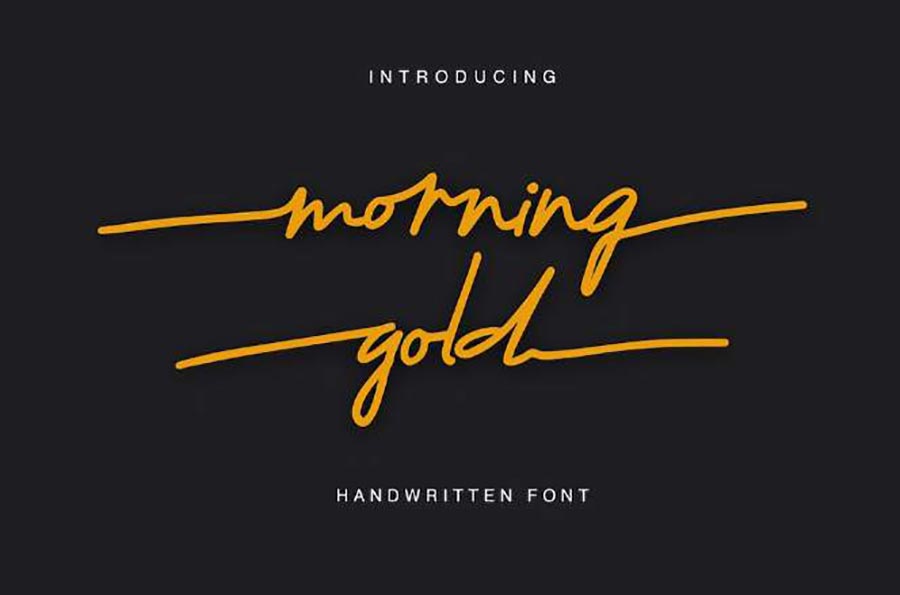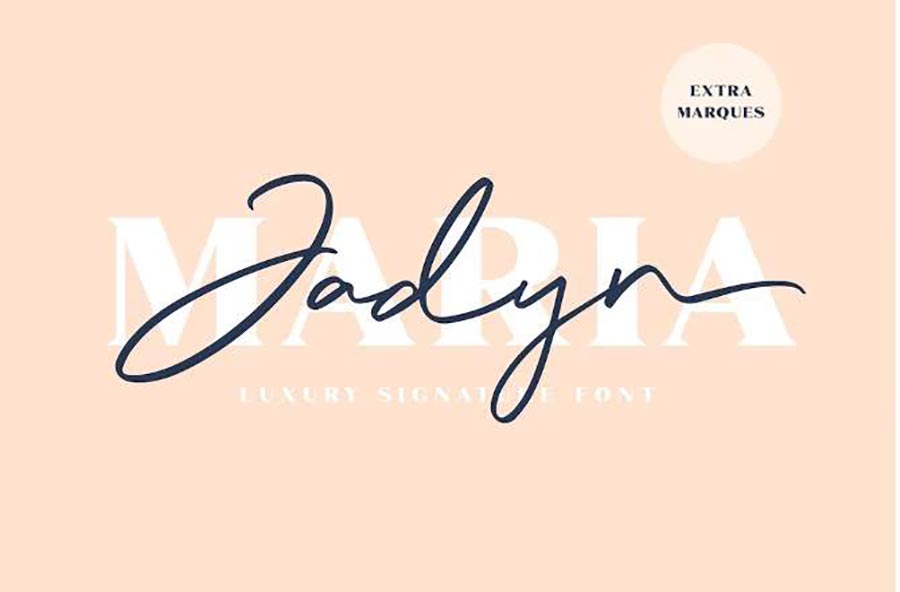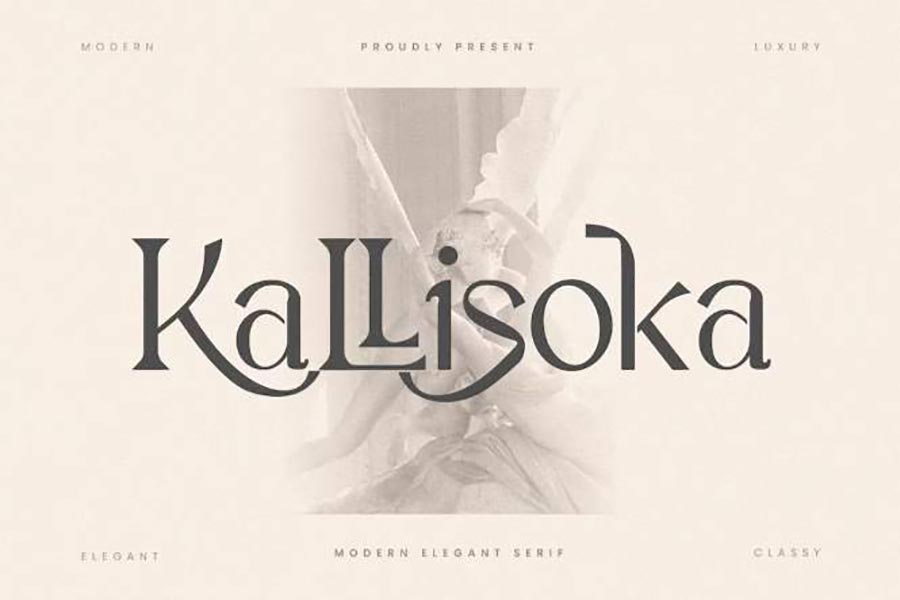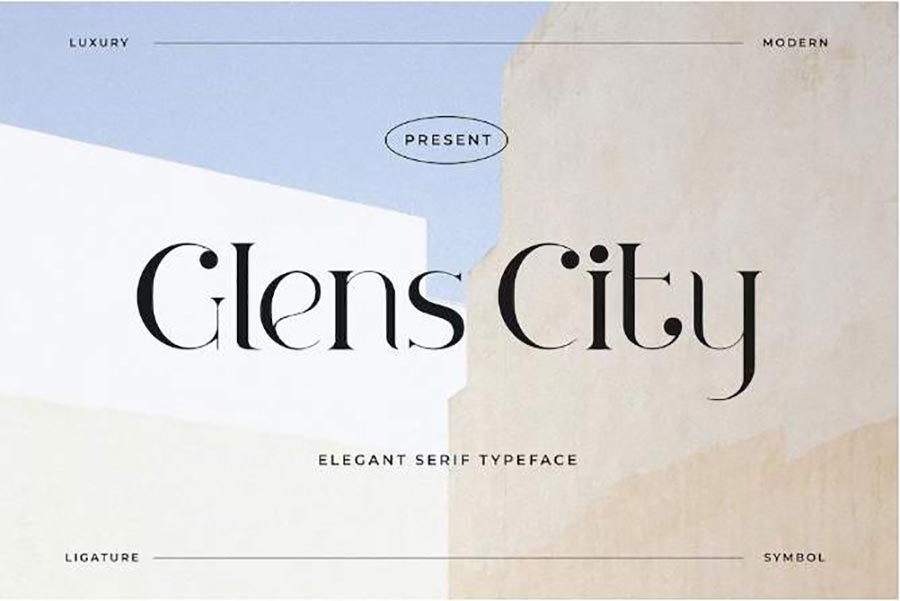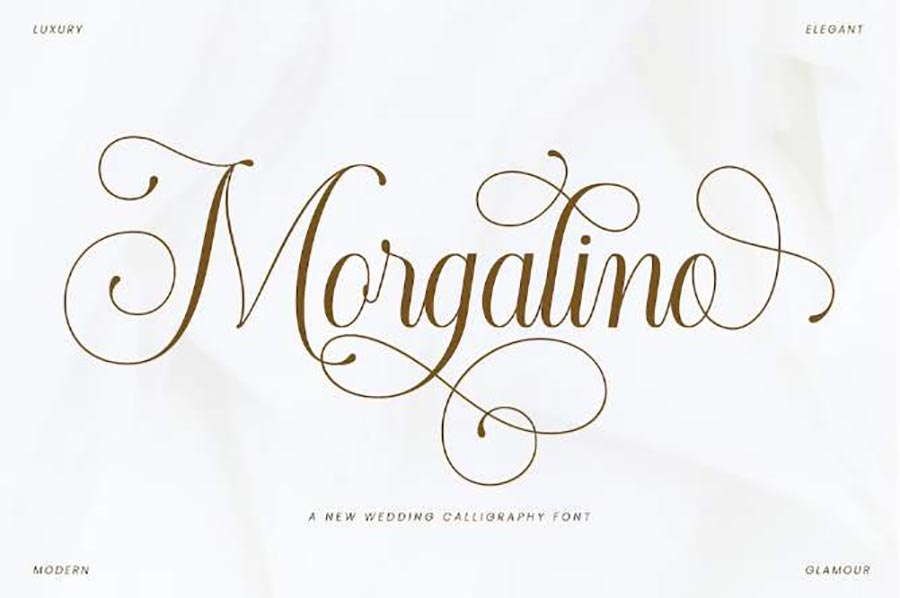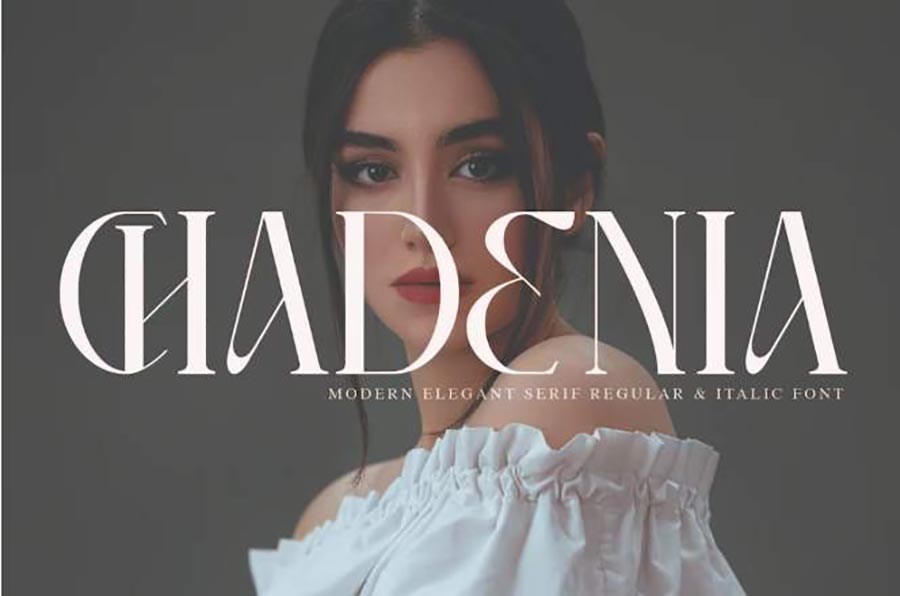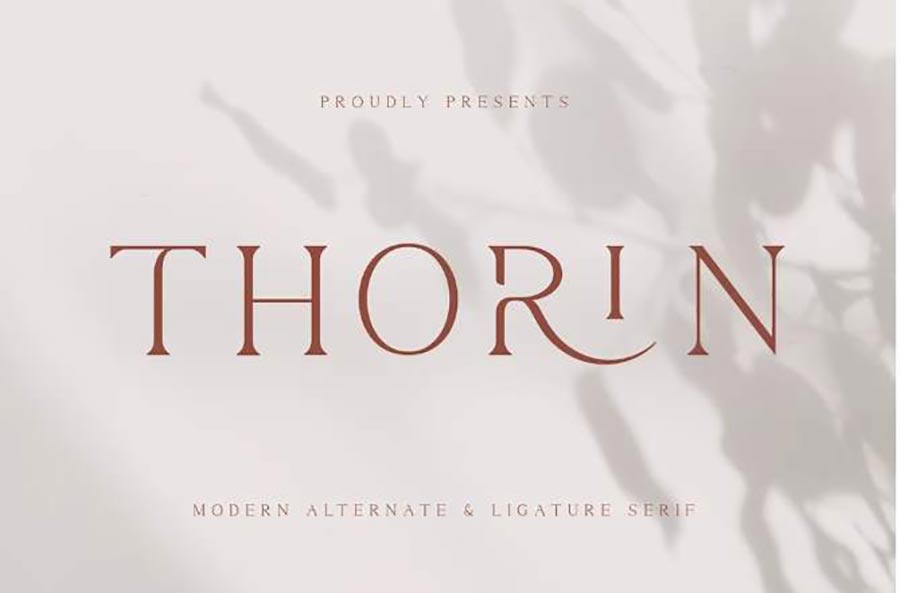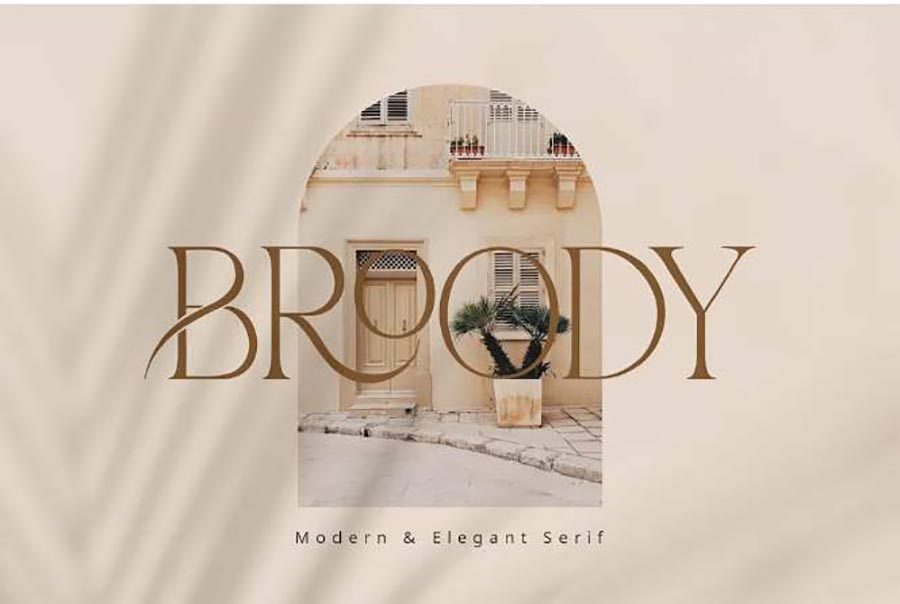
Bộ font chữ Luxury từ sadesign.vn là lựa chọn hoàn hảo cho những dự án thiết kế mang phong cách sang trọng và đẳng cấp. Các font chữ này giúp bạn tạo ra những sản phẩm thiết kế ấn tượng, chuyên nghiệp với vẻ đẹp tinh tế. Bài viết dưới đây sẽ hướng dẫn chi tiết cách tải và sử dụng bộ font Luxury miễn phí, mang đến cho bạn những lựa chọn thiết kế tuyệt vời.
1. Tại Sao Bộ Font Chữ Luxury Là Lựa Chọn Hoàn Hảo Cho Các Dự Án Thiết Kế?
Font chữ là một yếu tố quan trọng trong việc xây dựng và truyền tải thông điệp thiết kế. Không chỉ có tác dụng tăng tính thẩm mỹ cho sản phẩm, font chữ còn góp phần tạo dựng phong cách và bản sắc riêng cho thương hiệu.
Trong số rất nhiều font chữ hiện nay, font chữ Luxury nổi bật với thiết kế tinh tế, sang trọng và đẳng cấp. Đây là lựa chọn hoàn hảo cho những ai muốn tạo ra các thiết kế thể hiện sự sang trọng, quý phái như trong các dự án thiết kế logo, thiệp mời, poster, hay các ấn phẩm quảng cáo cao cấp.
Bộ font Luxury miễn phí từ sadesign.vn cung cấp cho bạn những lựa chọn tuyệt vời để tạo nên những sản phẩm thiết kế đẳng cấp, từ các chiến dịch marketing cho đến xây dựng thương hiệu. Bộ font này có thể giúp bạn nâng tầm các sản phẩm thiết kế, mang lại ấn tượng mạnh mẽ với đối tượng khách hàng.
2. Lợi Ích Khi Sử Dụng Bộ Font Chữ Luxury Miễn Phí
Tổng hợp bộ font Luxury miễn phí được chia sẻ từ Sadesign gồm có:
1. Thiết Kế Sang Trọng và Đẳng Cấp
Một trong những điểm mạnh nổi bật của font chữ Luxury là khả năng mang lại cảm giác sang trọng và đẳng cấp. Font chữ này rất phù hợp cho những dự án thiết kế đòi hỏi tính chuyên nghiệp và vẻ đẹp tinh tế. Các dòng font của bộ Luxury đều có đường nét mềm mại, thanh thoát, tạo cảm giác quý phái mà vẫn dễ đọc.
2. Phù Hợp Với Nhiều Dự Án Thiết Kế Cao Cấp
Bộ font Luxury không chỉ đẹp mà còn rất linh hoạt, phù hợp với nhiều loại thiết kế khác nhau. Bạn có thể sử dụng chúng cho logobộ nhận diện thương hiệuthiệp mờiposter sự kiệnbanner quảng cáo, hay thậm chí là in ấn bao bì sản phẩm. Với sự đa dạng về kiểu dáng và phong cách, font Luxury có thể dễ dàng kết hợp với các yếu tố thiết kế khác để tạo ra những sản phẩm bắt mắt và ấn tượng.
3. Dễ Dàng Chỉnh Sửa và Tùy Biến
Các font chữ Luxury đều có tính linh hoạt cao khi chỉnh sửa, bạn có thể thay đổi kích thước, màu sắc, thậm chí là tạo hiệu ứng đổ bóng hoặc các chi tiết đồ họa khác để phù hợp với nhu cầu thiết kế. Điều này giúp bạn dễ dàng áp dụng font trong nhiều dự án khác nhau mà không cần phải lo lắng về việc phù hợp với các yếu tố khác trong thiết kế.
4. Tính Độc Đáo và Mới Lạ
Mỗi bộ font Luxury đều mang đến một vẻ đẹp độc đáo, khác biệt so với những font chữ phổ biến. Sự khác biệt này giúp bạn tạo ra các thiết kế riêng biệt, nổi bật trong mắt khách hàng. Những mẫu font này rất thích hợp cho các dự án thiết kế đòi hỏi tính sáng tạo và muốn tạo dấu ấn riêng biệt trên thị trường.
Một số mẫu font chữ Luxury độc đáo, miễn phí tại Sadesign:
3. Kết Luận